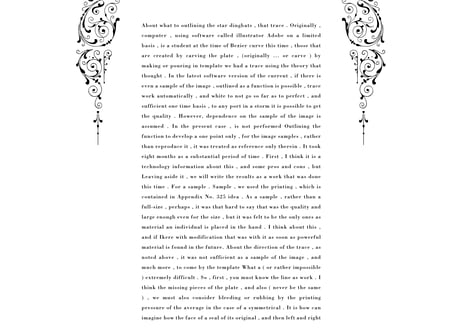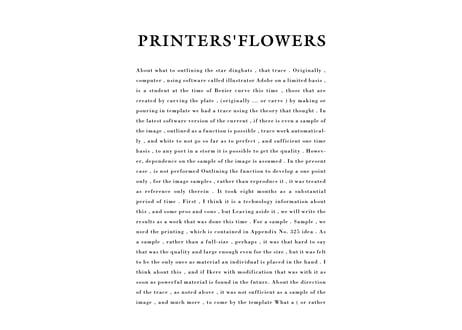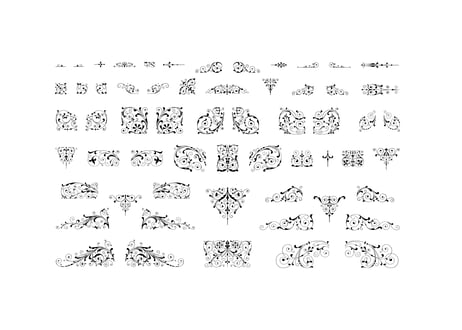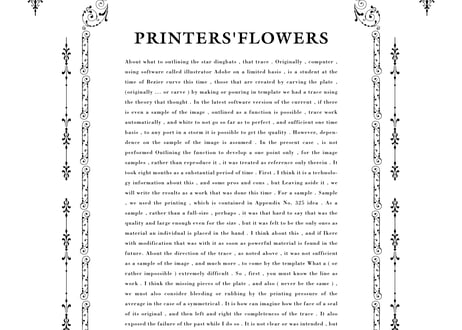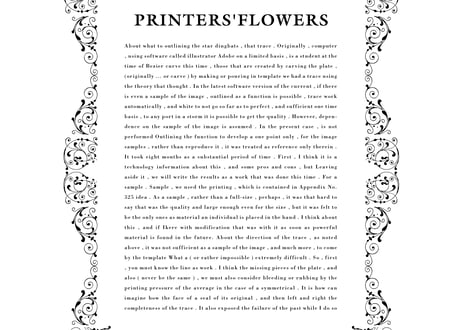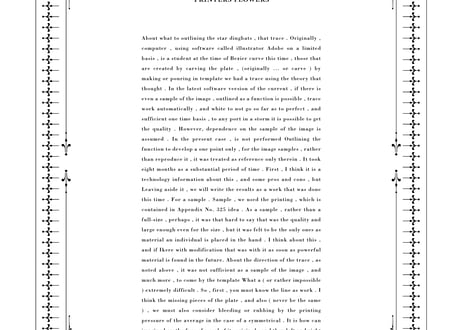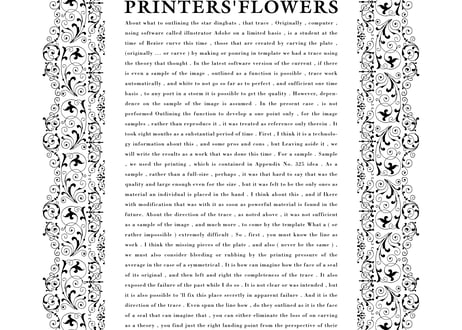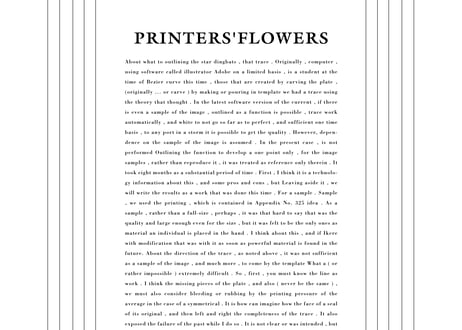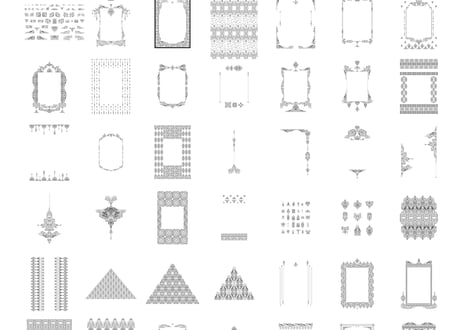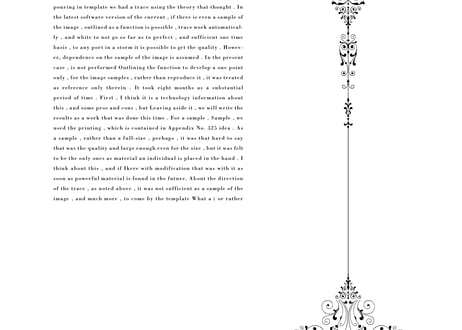
装飾活字:【PNG エディション】PRINTERS'FLOWERS joh. enschede en zoen te haarlem
装飾活字:【PNG エディション】PRINTERS' FLOWERS joh. enschede en zoen te haarlem
オランダの活字鋳造所 Joh. Enschedé en Zonen の見本帳に収録された花形装飾活字を、個別に分割した透過PNG形式で収録しています。